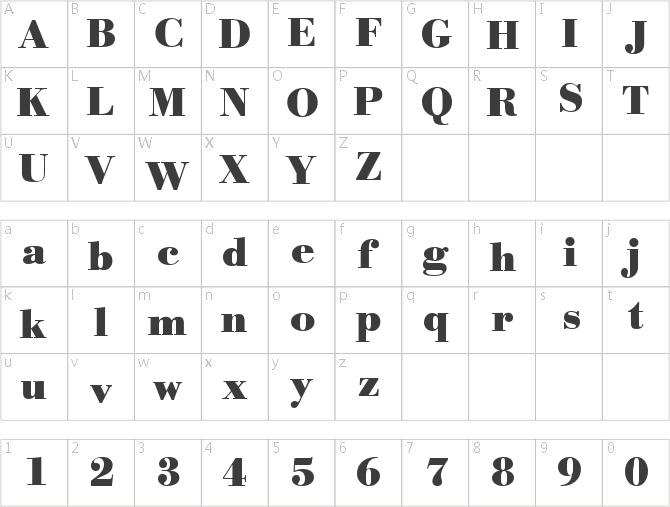
ModernBodoniHeavy 詳情頁(yè)
ModernBodoniHeavy
ModernBodoniHeavy字體字庫(kù)是一款讓人賞心悅目、百看不厭的英文字體,適合各類廣告和產(chǎn)品包裝設(shè)計(jì)應(yīng)用,字體大小0.05MB,格式為ttf字體,上傳用戶是后天的昨天,作者/版權(quán)方為未知